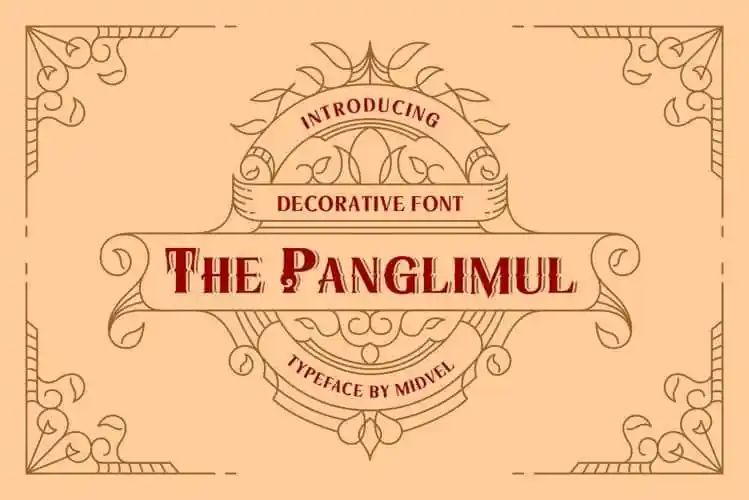
The Panglimul Display Font – Fonte Grátis
The Panglimul Display Font
A nova fonte The Panglimul Display é uma jóia do design que traz elementos vintage para seus logotipos, tornando-os mais interessantes e atraentes. Inspirada nos movimentos artísticos decorativos e arquitetônicos da década de 20, essa fonte oferece um toque especial com alternativas de caracteres únicas e suporte multilíngue para uma experiência fluida em qualquer idioma. Além disso, você recebe como bonus um conjunto de vetores ornamentais, permitindo que você combine-os com a fonte para criar designs encantadores e arrojados. A The Panglimul Display é perfeita tanto para criações de etiquetas de produtos quanto para o nome de lojas, cartazes, design de talheres, sinais de casamentos ou até mesmo desenhos de roupas, oferecendo inúmeras possibilidades criativas e modernas.